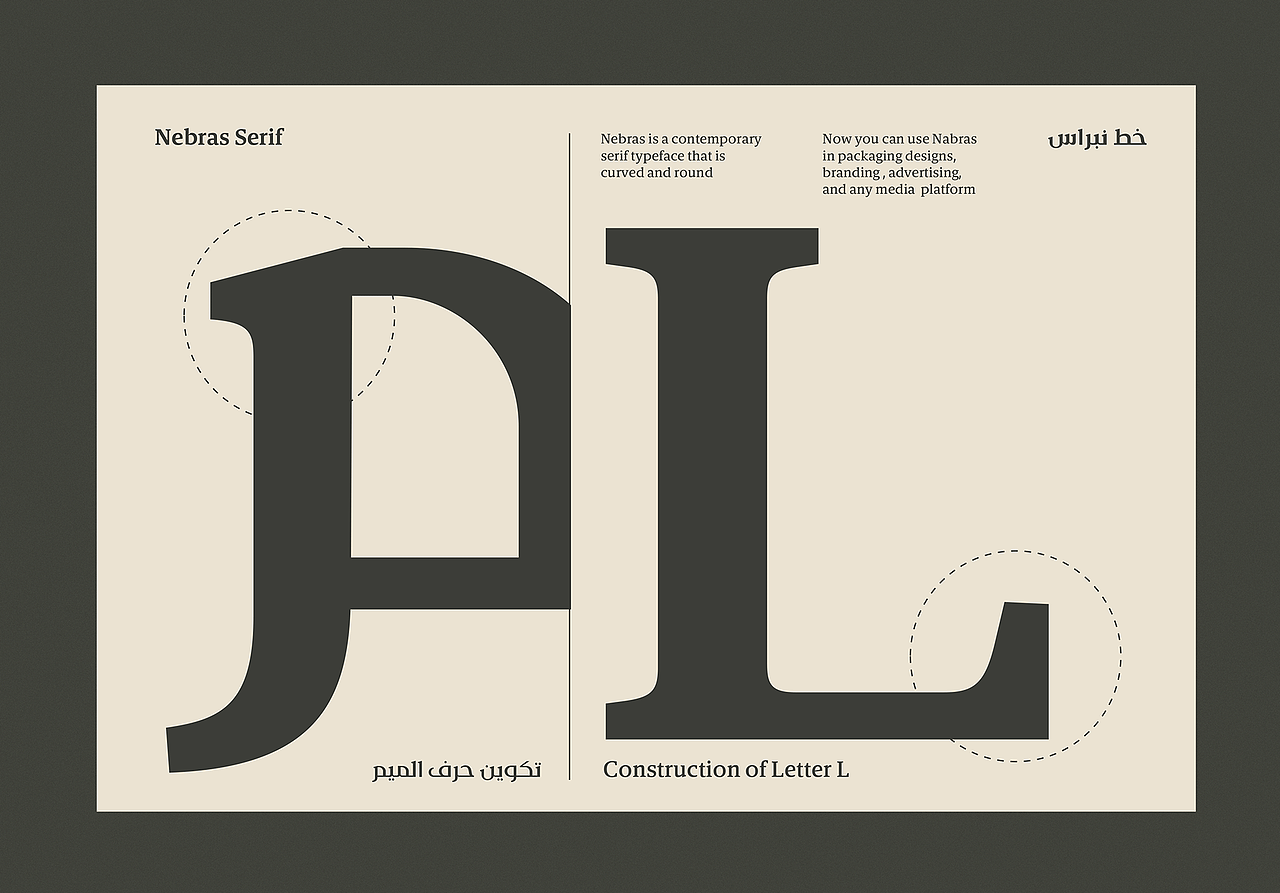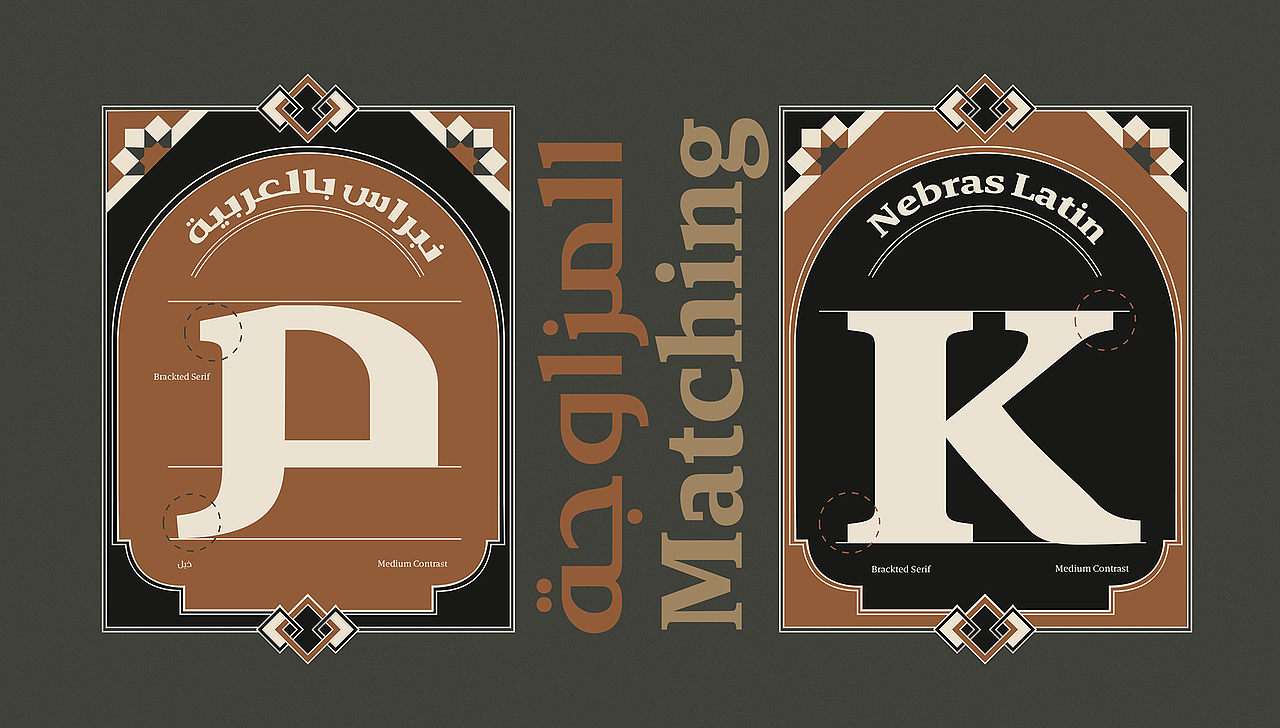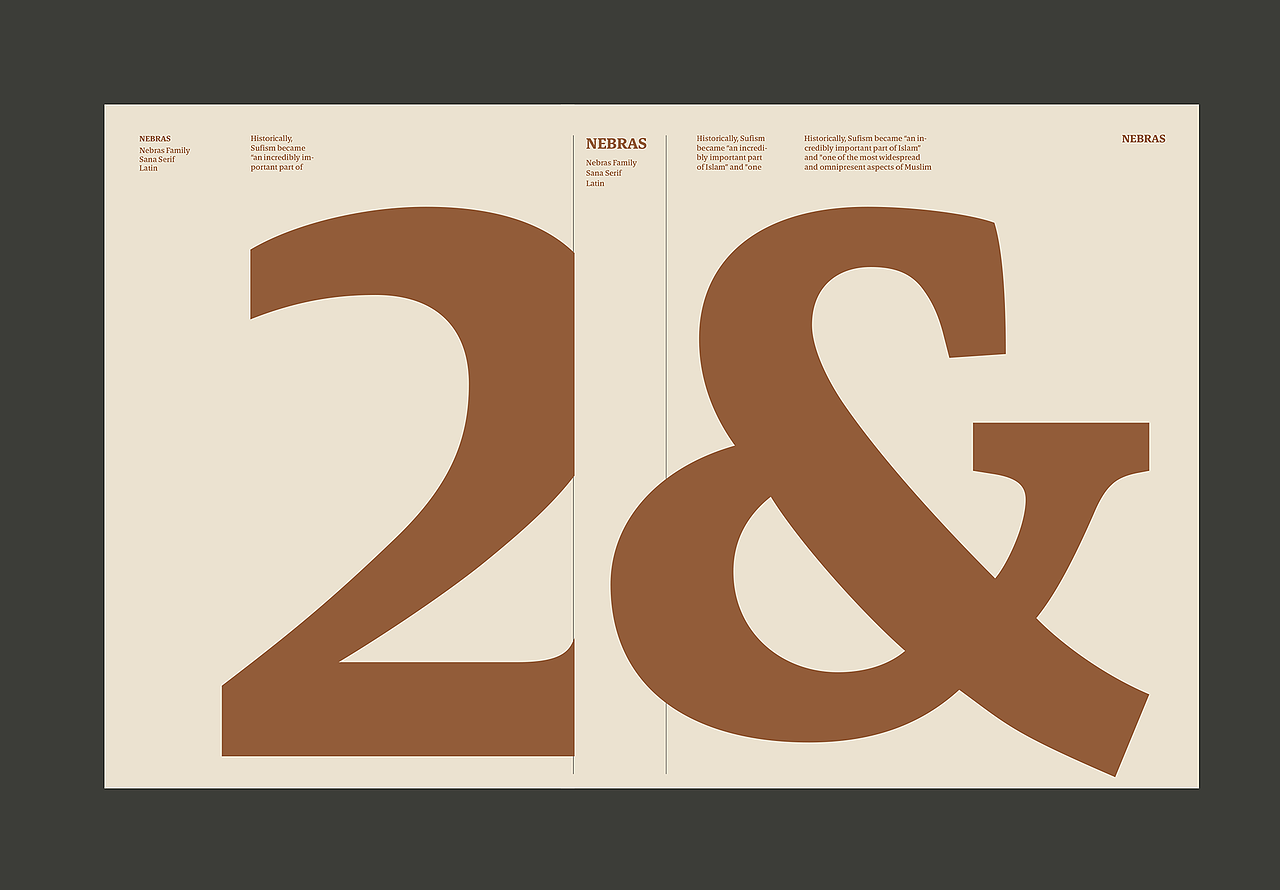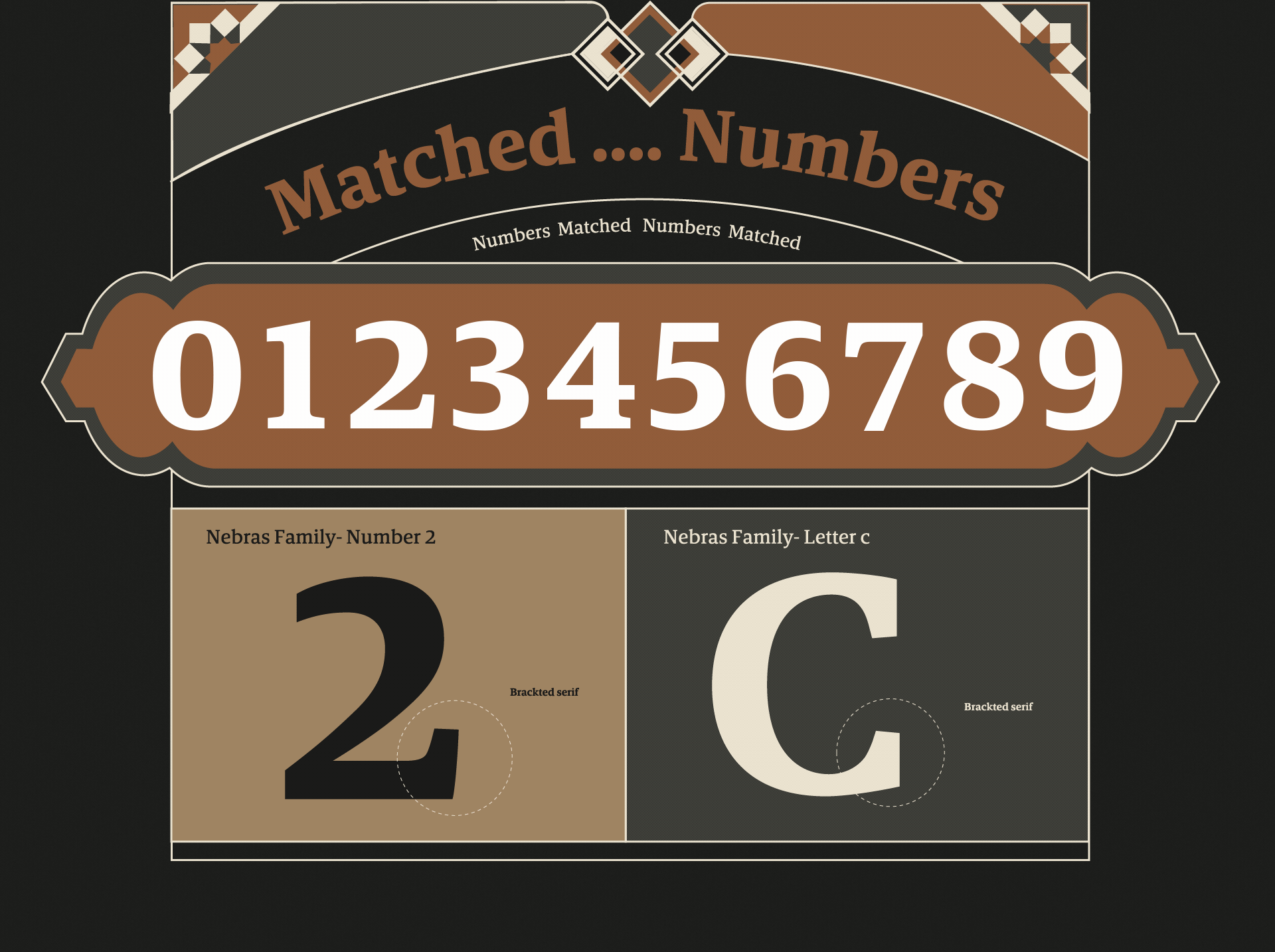
Nebras 字体
Baianater
Nebras 是一种当代的无衬线字体,它是弯曲的和圆形的,但它的替代字体也是直的和前卫的。 它有 3 种不同的宽度和 9 种重量,支持 +50 种语言,从更经济但清晰的压缩样式到华丽的粗体和扩展重量。 现在,您可以将 Nabras 用于包装设计、品牌推广、广告和任何您想要对比鲜明、鲜明而优雅且具有时尚感的媒体平台,它也适用于小型正文和标题。